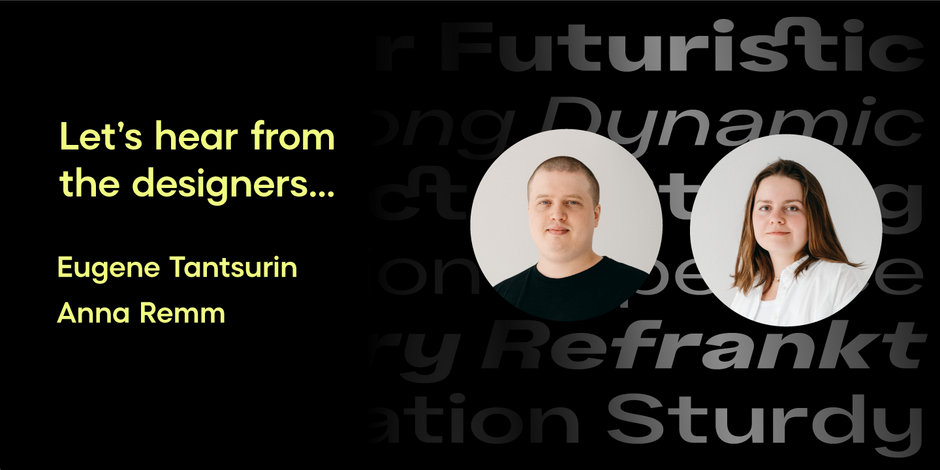
#24 Refrankt von Groteskly Yours
Q1:Woher kam die Idee für die Schrift? Wollten Sie einen bestimmten Verwendungszweck oder eine bestimmte Suite der Anwendung ansprechen? Hatten Sie dieses Design schon eine Weile im Kopf?
Ans:Im Gegensatz zu unseren früheren Projekten hatten wir für Refrankt von Anfang an eine klare Vision. Die Idee war, eine Schriftfamilie zu entwerfen, die unverkennbar futuristisch ist, aber dennoch die Lesbarkeit beibehält, die man mit serifenlosen Schriften verbindet. Sowohl die Struktur der Familie als auch ihr Charakter stellen sicher, dass Refrankt für die Herausforderungen der sich schnell entwickelnden digitalen Welt gerüstet ist. Wir denken, dass Refrankt eine ausgezeichnete Wahl für Projekte ist, die eine Schrift mit zeitgemäßer Ästhetik und funktionellem Design erfordern.
Q2:Was sollten Grafik-Kommunikatoren über die Schriftart wissen, oder wie wird die Schriftfamilie ihnen helfen, bessere Designs zu erstellen?
Ans:Wir glauben, dass Designer von der Vielseitigkeit von Refrankt angenehm überrascht sein werden. Die leichteren Schnitte weisen einen minimalen Kontrast auf und wirken fast monolinear, während die kräftigeren Stile robuster und markanter sind. Diese Palette an Stilen wird durch die Einbeziehung einer variablen Schriftart noch erweitert, die es Designern ermöglicht, ihre Entwürfe fein abzustimmen und komplexe typografische Systeme zu erstellen. Darüber hinaus unterstützt Refrankt mehrere OpenType-Funktionen, die für Designer, die Wert auf Einzigartigkeit und Kreativität legen, ein unschätzbares Werkzeug sein können.